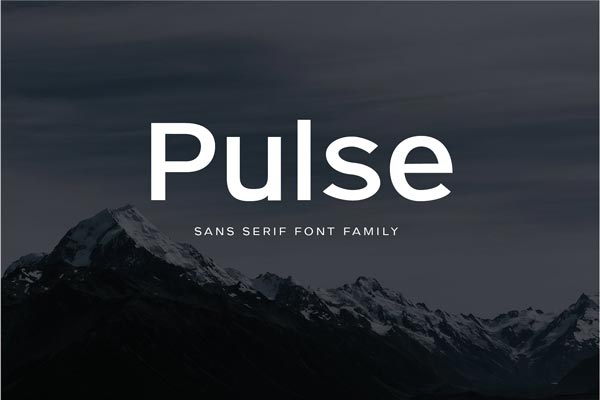
Pulse – پالس یک قلم و فونت لاتین بسیار حرفه ای و جذاب است که توسط Cassandra Cappello طراحی شده و در Creative Market با قیمت 22 دلار بفروش میرسد. این مجموعه فونت حرفه ای و کاربردی هم اکنون بصورت کامل و رایگان از نال اکس آماده دانلود و استفاده شما کاربران گرامی میباشد.
ویژگی های فونت :
- طراحی دقیق و کاملا حرفه ای
- نمایش بی نقص تمامی حروف و اعداد بدون مشکل
- مناسب برای انواع طرح های گرافیکی
- مناسب برای ساخت و طراحی فونت، پوستر، لیبل و …
پالس حداقل یک کلاسی بدون حروف بزرگ است. این شخصیت کمی دارد و می تواند برای هر دو هدر و کپی بدن استفاده شود. این فونت شامل تمام کاراکترهای لاتین (از جمله لهجه ها)، اعداد، کاراکترهای خاص و نشانه گذاری است.